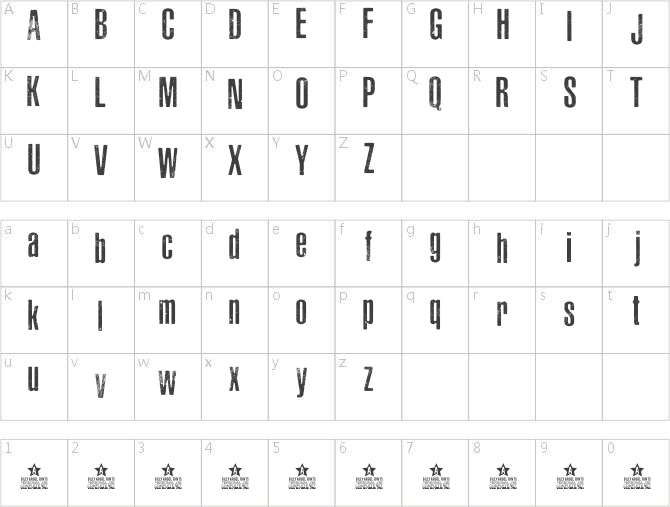
ASPHALTIC SCRATCH ROUNDED PERSON
ASPHALTIC SCRATCH ROUNDED PERSON介紹
ASPHALTIC SCRATCH ROUNDED PERSON字體字庫是一款讓人賞心悅目、百看不厭的英文字體,適合各類廣告和產品包裝設計應用,字體大小1.36MB,格式為ttf字體,上傳用戶是得·岸,作者/版權方為未知